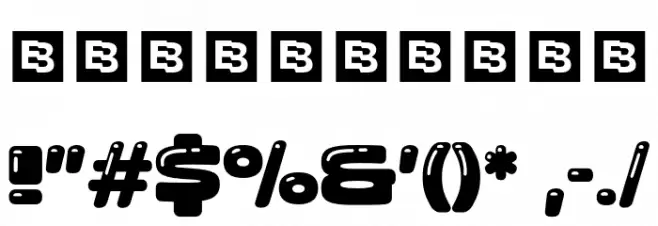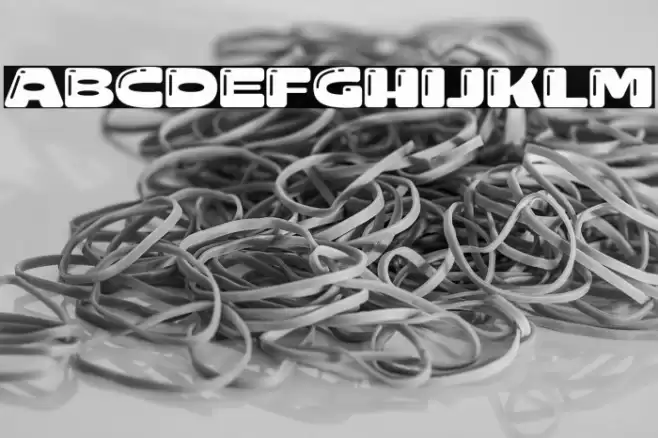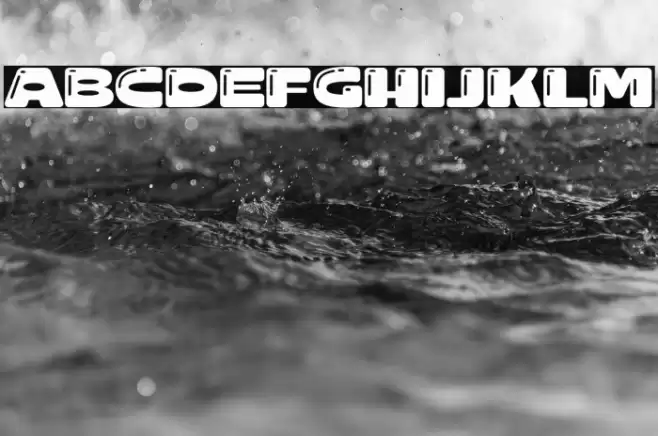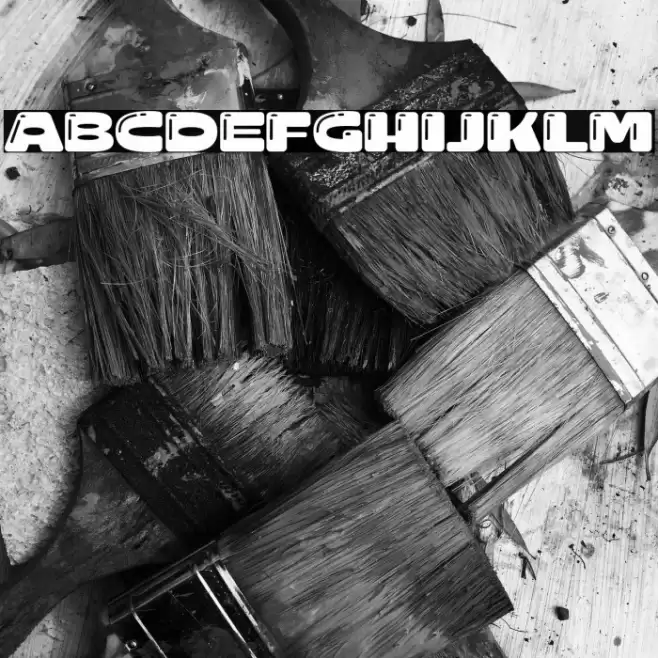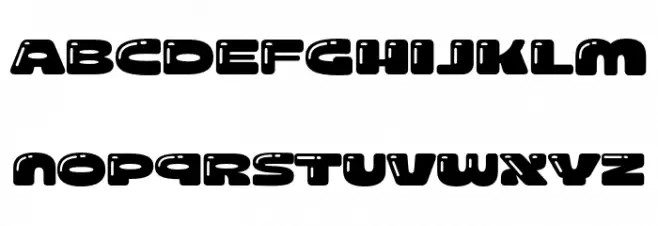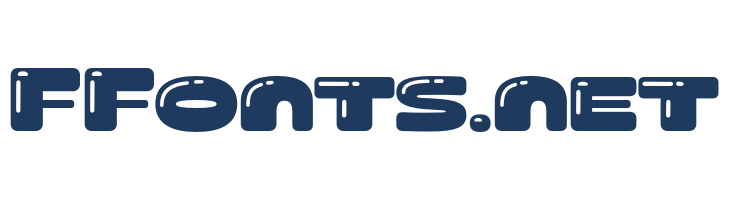
GrunoBubbleTrial-Regular Font
| Schriften Familie | Gruno Bubble Trial |
| Gesamtstil | Playful, Whimsical |
| Vorgeschlagene Projekte | Ideal for children's books, playful branding, party invitations, and creative posters. |